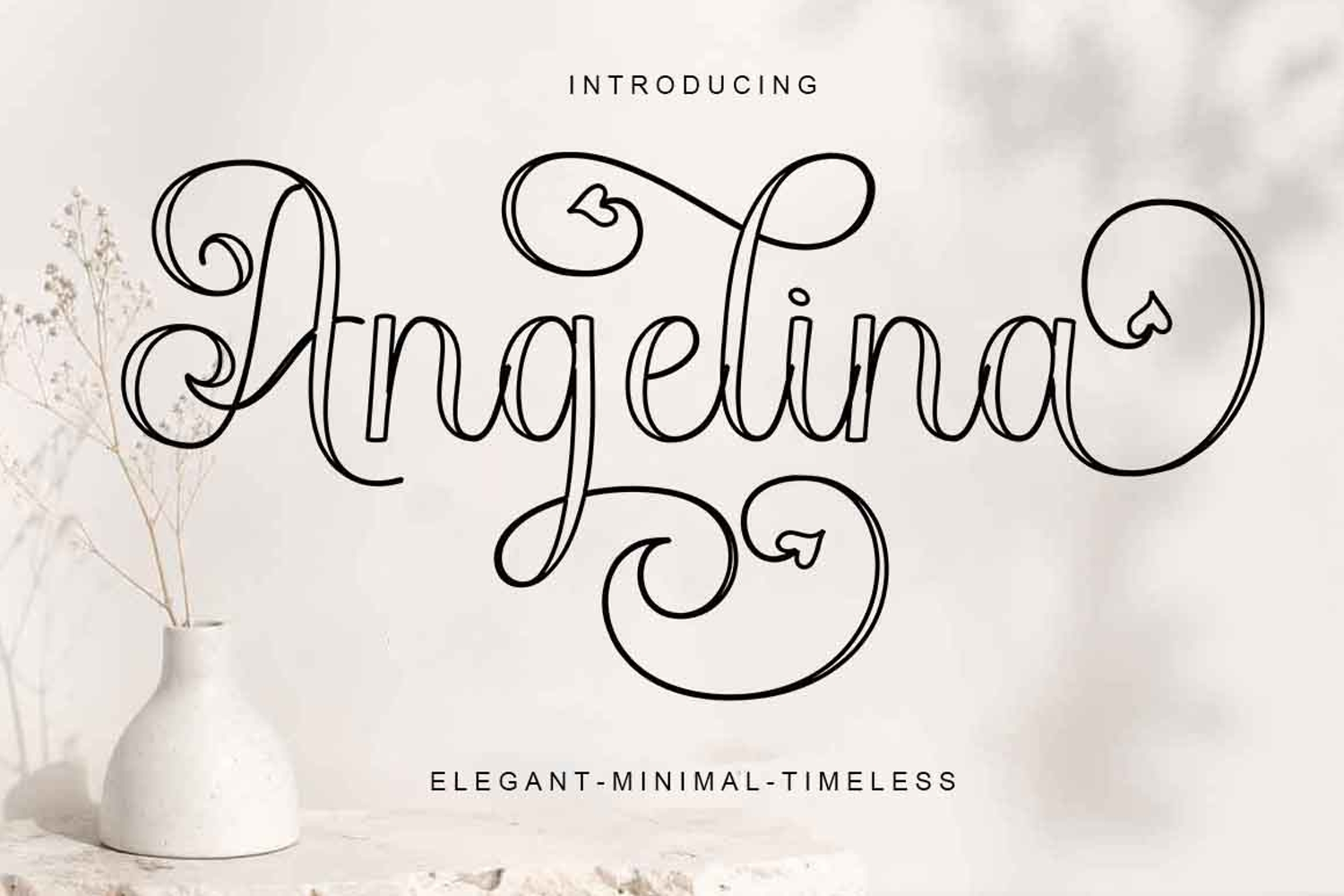
# Angelina – Font Skrip Elegan
Angelina adalah font skrip yang anggun dan elegan, dirancang untuk menghadirkan keindahan dan kecanggihan pada setiap proyek kreatif. Menampilkan goresan tulisan tangan yang halus, sapuan yang lembut, dan bentuk huruf yang tak lekang oleh waktu, font ini sangat cocok untuk menciptakan desain yang mewah dan romantis.
Baik Anda mendesain undangan pernikahan, branding, logo, kemasan, grafis media sosial, atau alat tulis premium, Angelina menambahkan sentuhan yang halus dan profesional yang membuat setiap desain menonjol.
### Cocok Untuk:
* Undangan Pernikahan
* Desain Merek & Logo
* Kemasan Kecantikan & Kosmetik
* Merek Fesyen
* Produk Butik & Mewah
* Kartu Ucapan
* Kutipan & Media Sosial
* Sampul Buku
* Judul Majalah
* Kemasan Produk
* Desain Tanda Tangan
* Tanda Air Fotografi
### Fitur:
* Huruf Kapital & Huruf Kecil
* Angka & Tanda Baca
* Hiasan Indah *
Angelina dirancang untuk memberikan desain Anda nuansa tulisan tangan yang mewah sekaligus mempertahankan keterbacaan yang sangat baik. Ini adalah pilihan ideal bagi desainer, pengrajin, dan profesional kreatif yang mencari font skrip elegan dengan tampilan abadi.